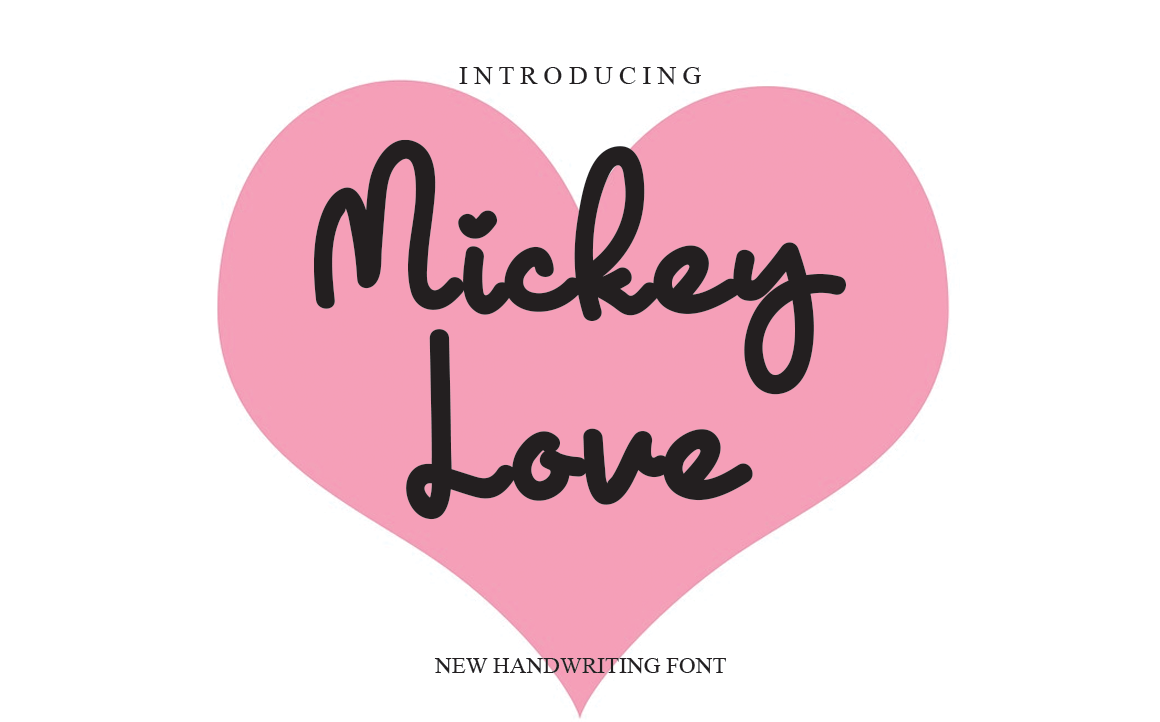
Através deste fonte amigável e divertida, você pode transformar qualquer ideia criativa em arte perfeita para sua plataforma Instagram ou projecto de escritura artesanal DIY. O Mickey Love Font é perfeito para aqueles que buscam uma fonte curvilínea, divertida e amigável para usar em qualquer projeto gráfico. Este font foi projetado com um toque descontraído e encantador, tornando-o ideal para criar um visual agradável que chama atenção no seu design. A versão handwritten deste font de arte Mickey Love irá enriquecer sua apresentação, transformando simples mensagens em verdadeiras obras de arte. Este é o font perfeito para aqueles que querem inovar e se destacarem na web. Não hesite em explorar a riqueza visual deste fonte Mickey Love Font, uma das muitas opções criativas disponíveis no design gráfico hoje.